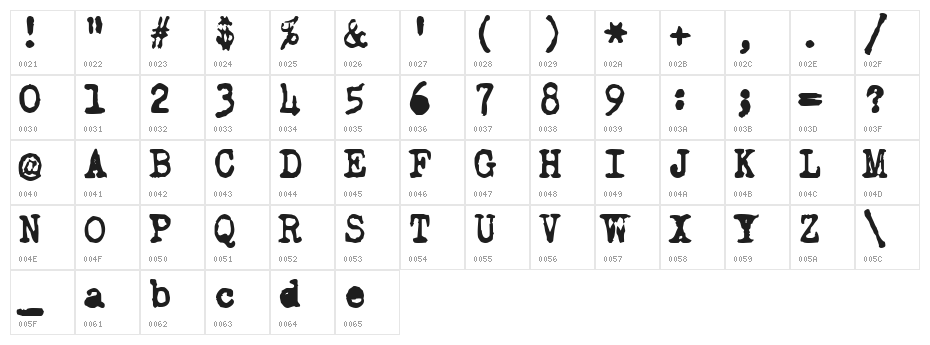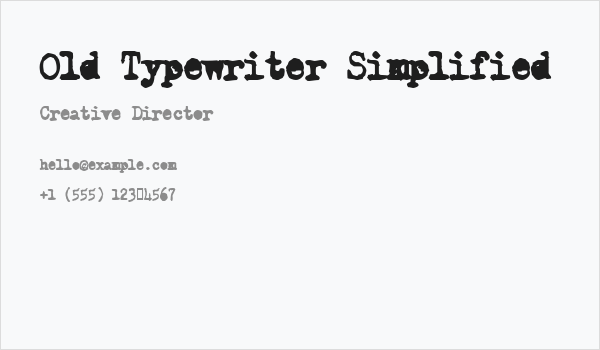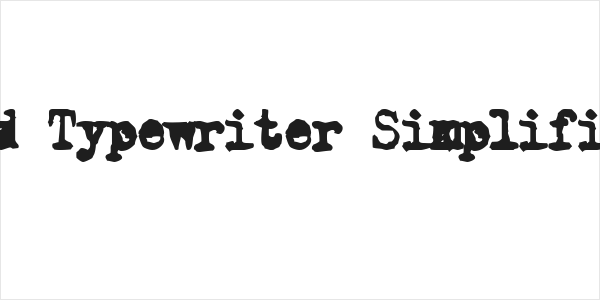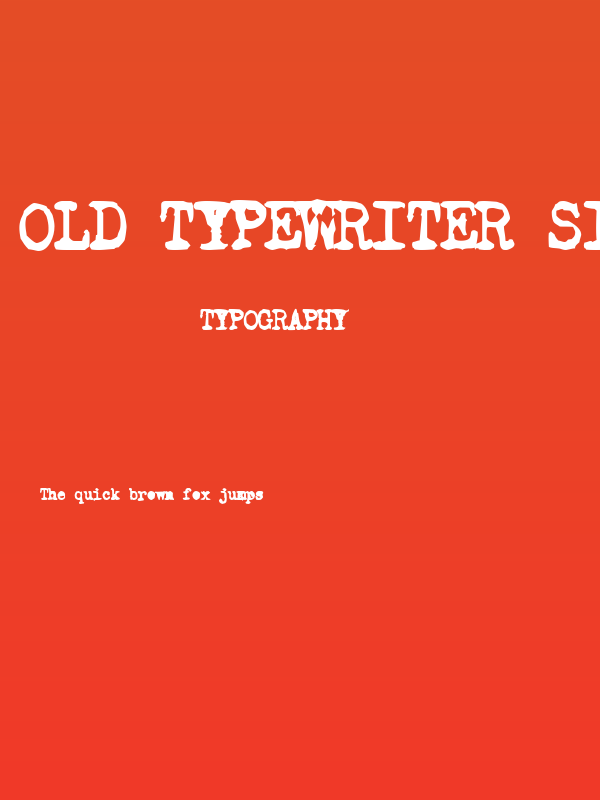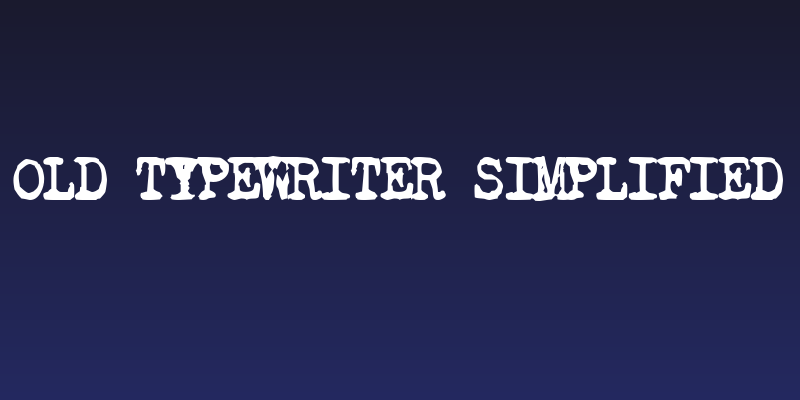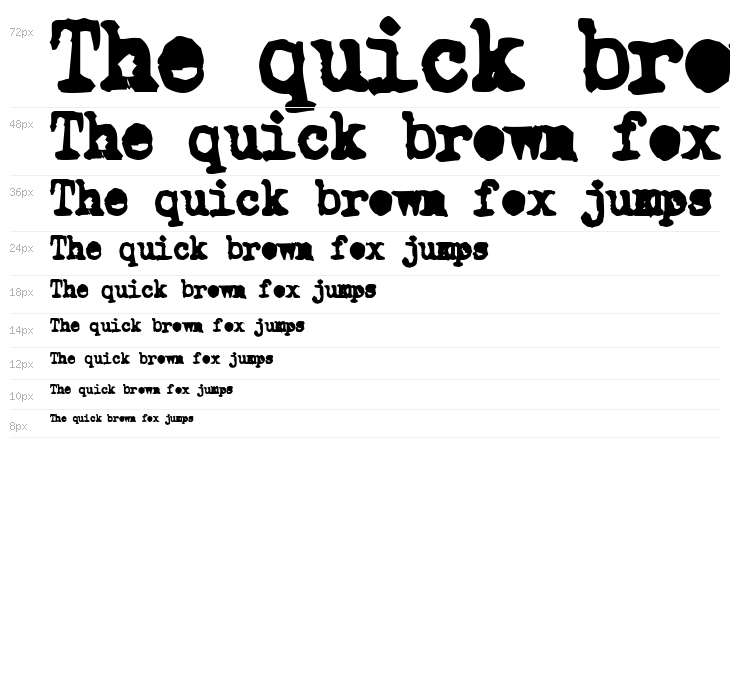
Old Typewriter Simplified Font
| Estilo general | Vintage |
| Proyectos propuestos | Ideal for retro-themed designs, vintage posters, typewriter-inspired branding, and creative writing projects. |
| Es fijo Pitch | Yes |